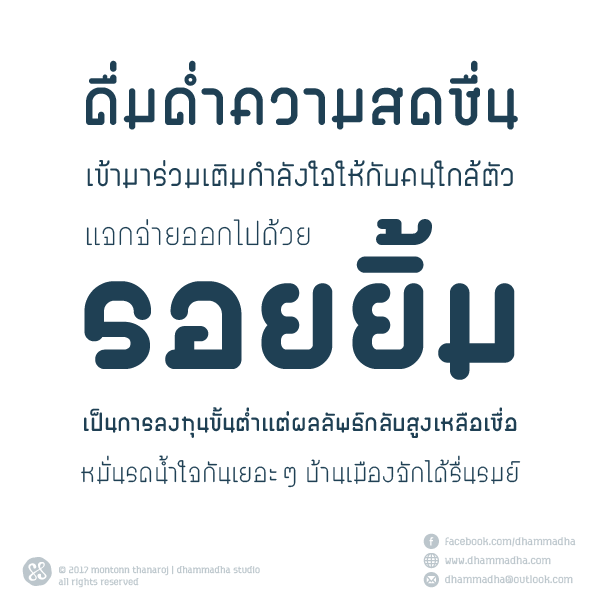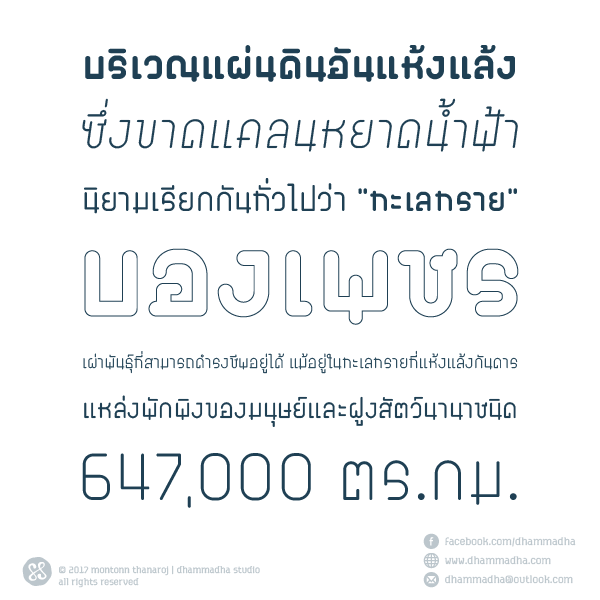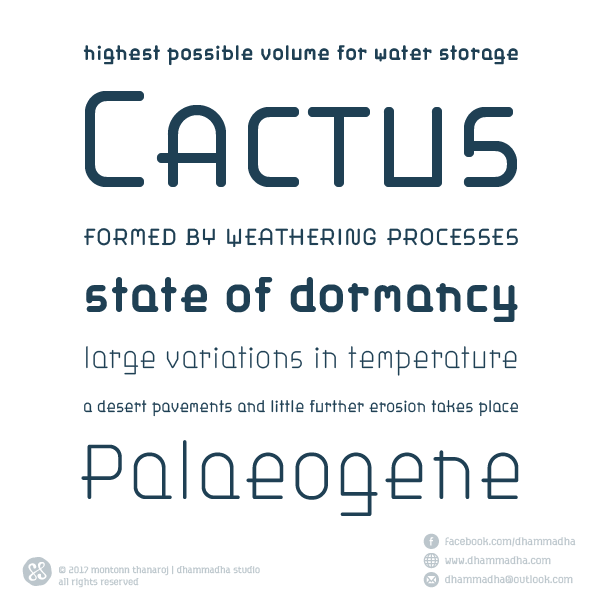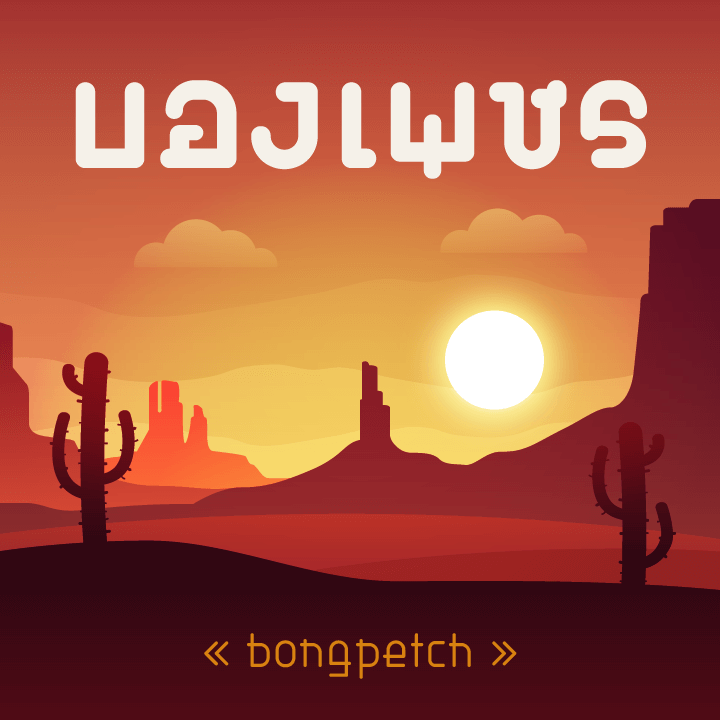
บองเพชร | bongpetch
เป็นชุดอักษรที่ดึงบุคลิกมาจากรูปร่างของต้นกระบองเพชร
ซึ่งมีลักษณะคล้ายกับการลากเส้นต่อจุด
แม้ว่าเมื่อนำมาพัฒนาเป็นชุดอักษรแล้วได้มีการลดทอนบุคลิกที่ว่าลงไป
แต่ก็ขอตั้งชื่อไว้ว่า “บองเพชร” พอให้ได้รู้ที่มาที่ไปครับ
ชุดอักษรประกอบด้วยฟอนต์ 4 น้ำหนัก พร้อมตัวเอียง
(thin / regular / bold / black)
bongpetch สามารถใช้งานภาษาไทยได้อย่างสมบูรณ์ ฟีเจอร์ใช้งานครอบคลุม
(OpenType / Ligature / Small Caps)